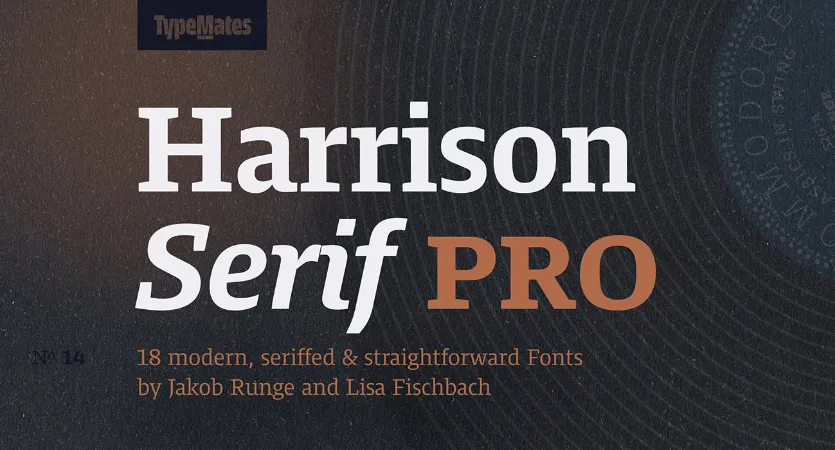
Harrison Serif Pro Font Family – Download Grátis
Estamos procurando uma Serif para um projeto de design novo? Ou talvez você esteja pensando em ter uma coleção de fontes de alto nível. Introduzimos a Harrison Serif Pro Font Family! Harrison Serif Pro foi projetada pelo TypeMates e é uma serif robusta mas com contraste de linhas grossas que combina um método racional e eficiente com um tom amigável. Uma tipografia repleta de nuances, as levei cortadas e ocasionalmente estendidas podem ser carregadas na parte afetuosa da Harrison Serif ao mesmo tempo em que contrastam com a natureza direta dos traços retos, os aberturas horizontais e a curvatura quadrada do tipo. Esta fonte é perfeita para seus projetos de design, oferecendo uma mistura harmoniosa de modernidade e personalização. Descubra agora Harrison Serif Pro e transforme sua próxima criação digital!